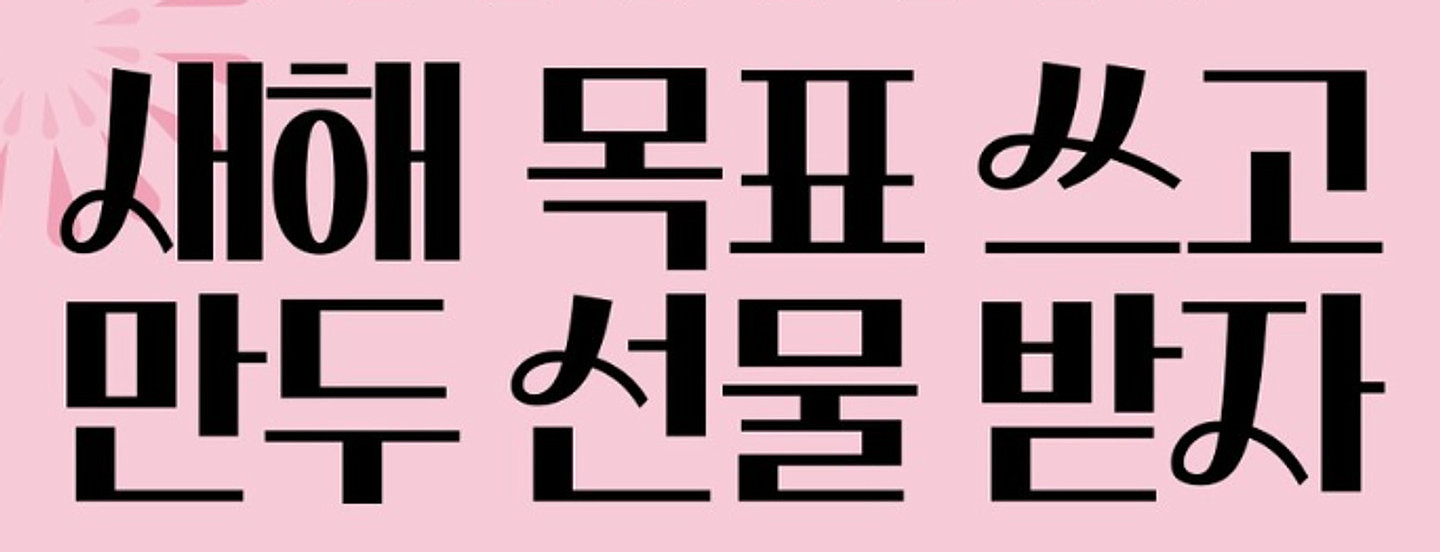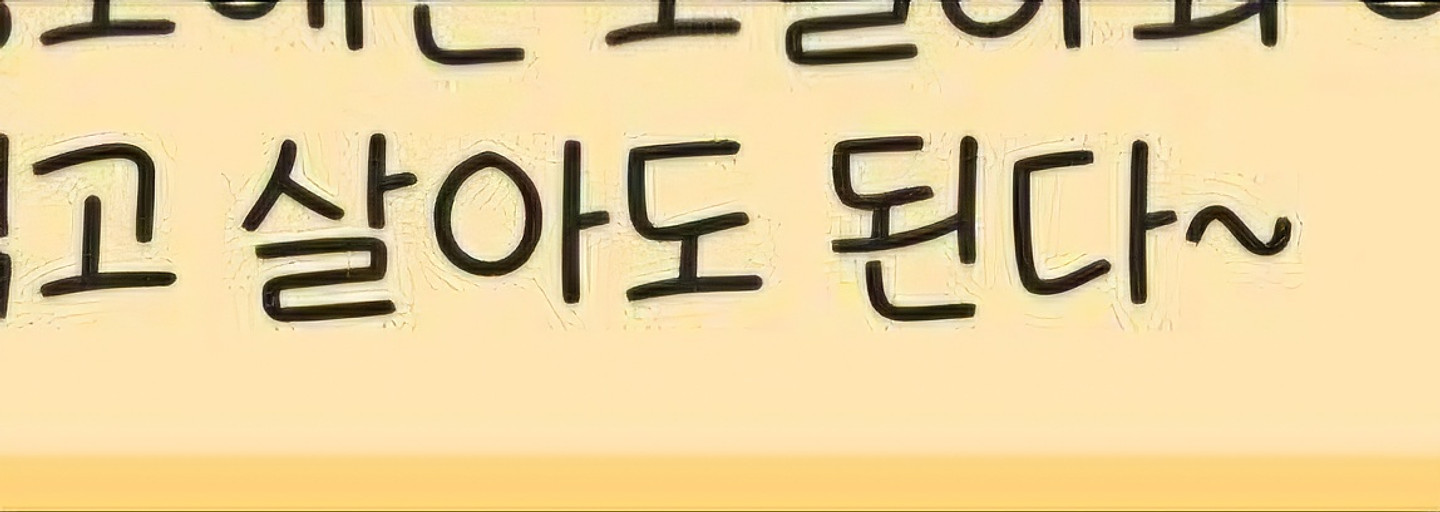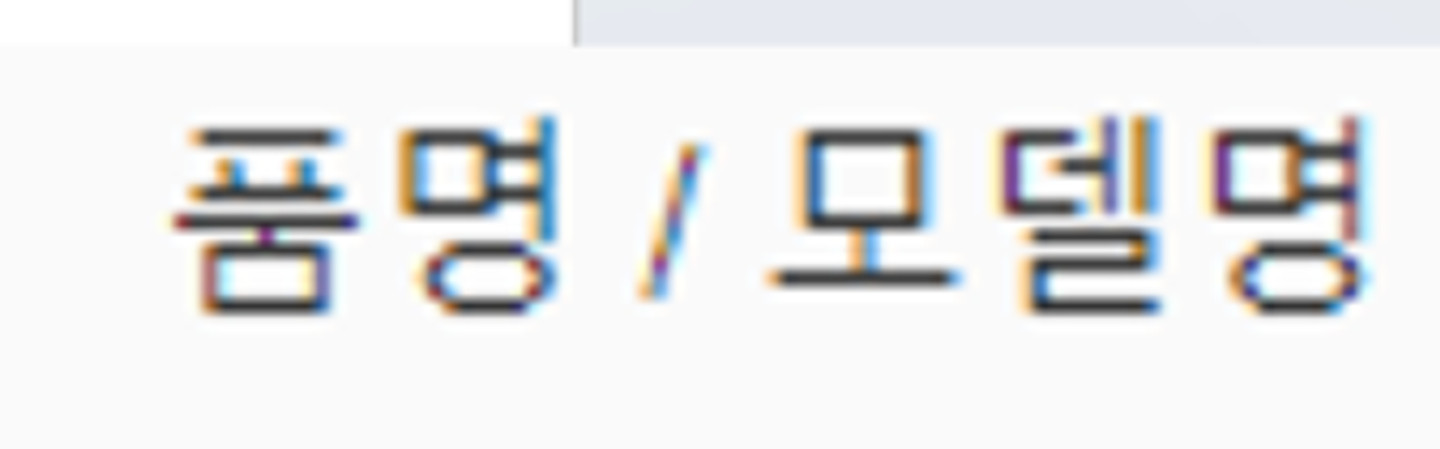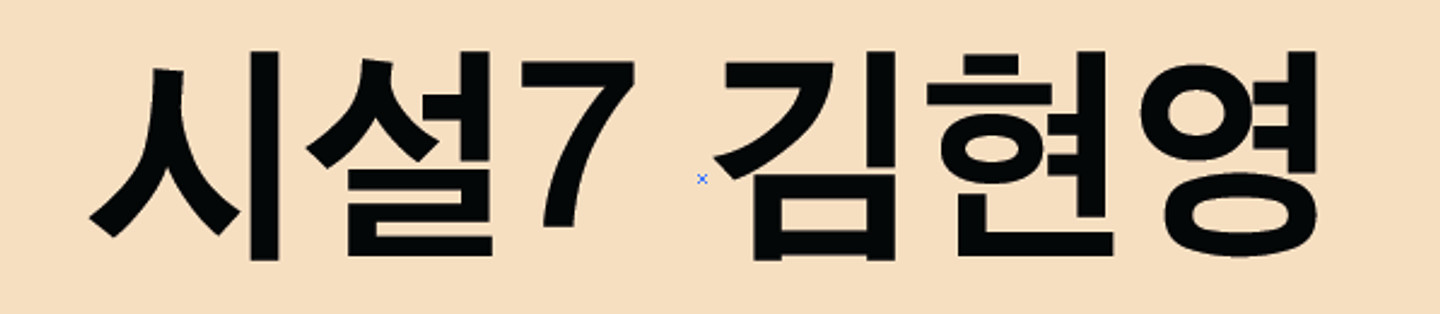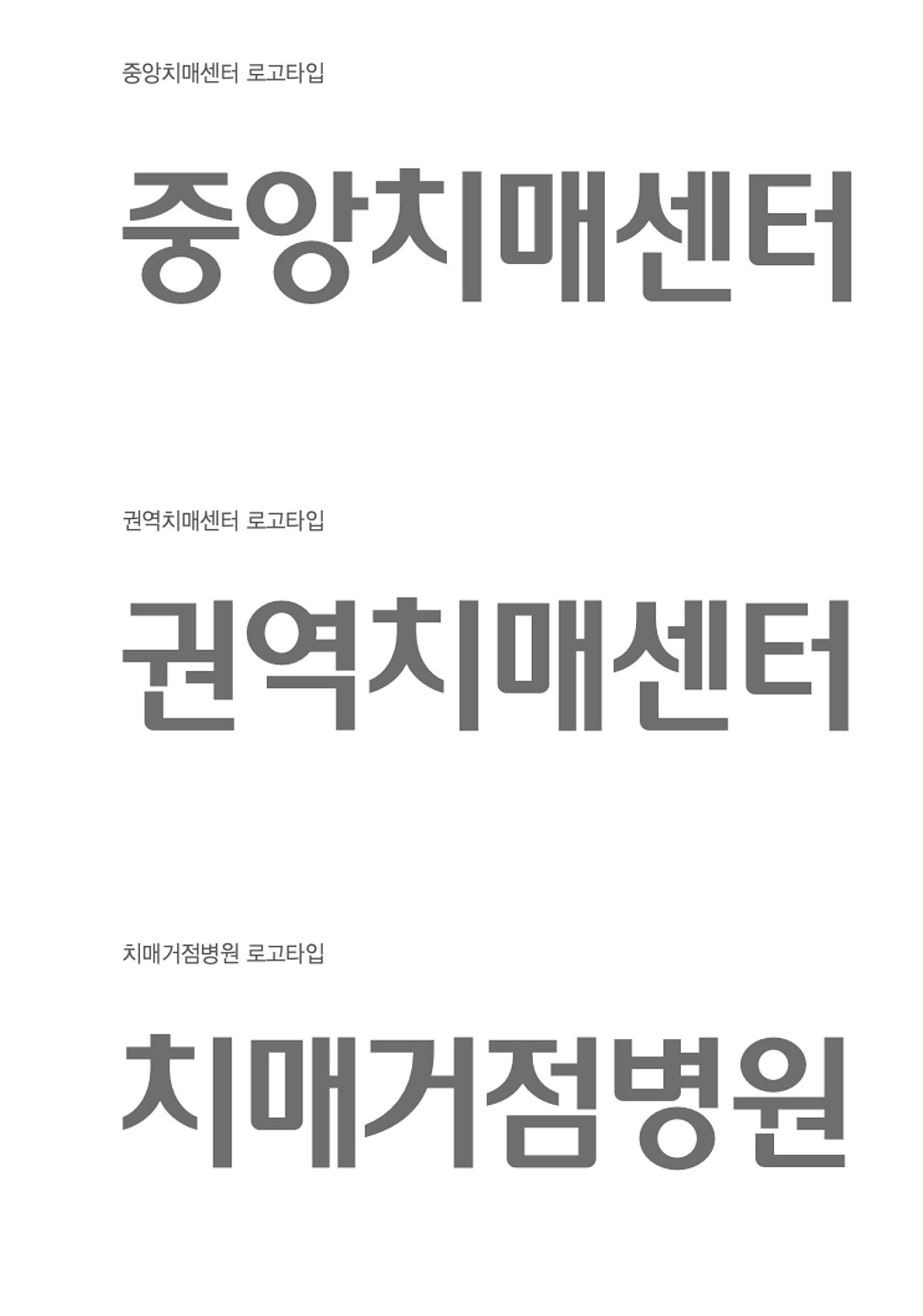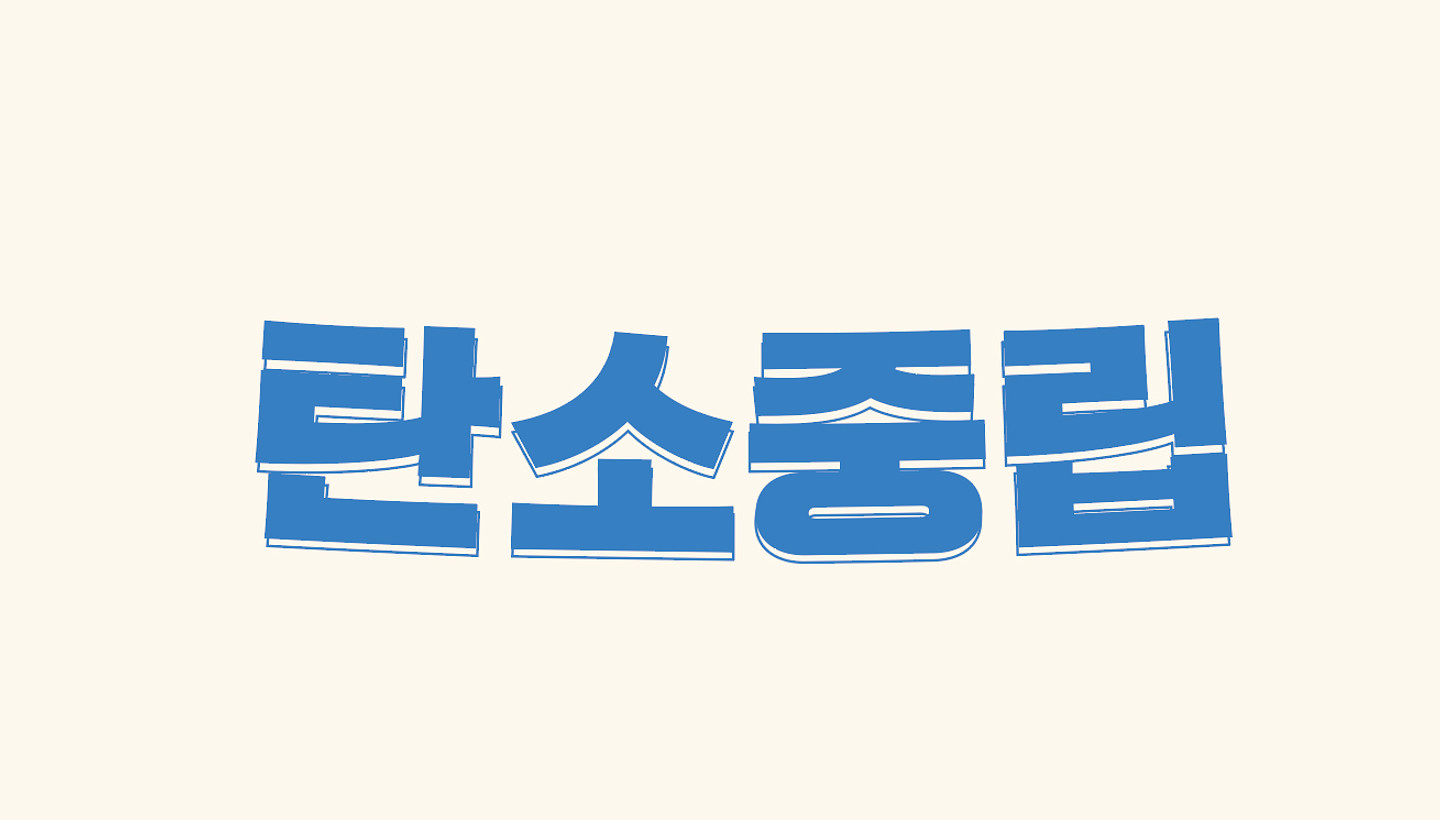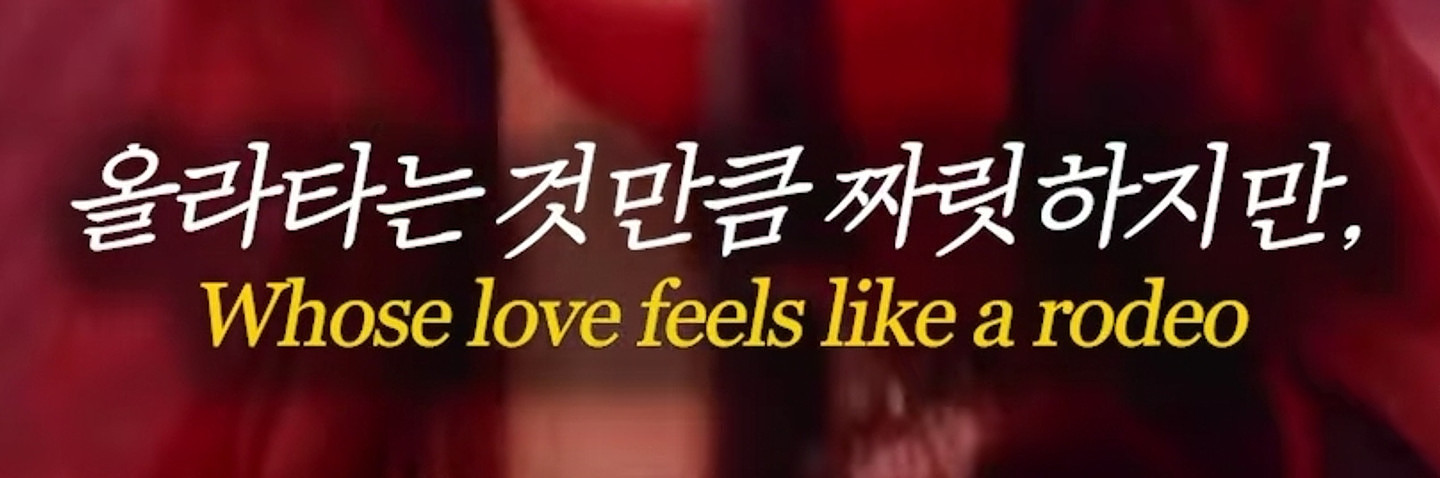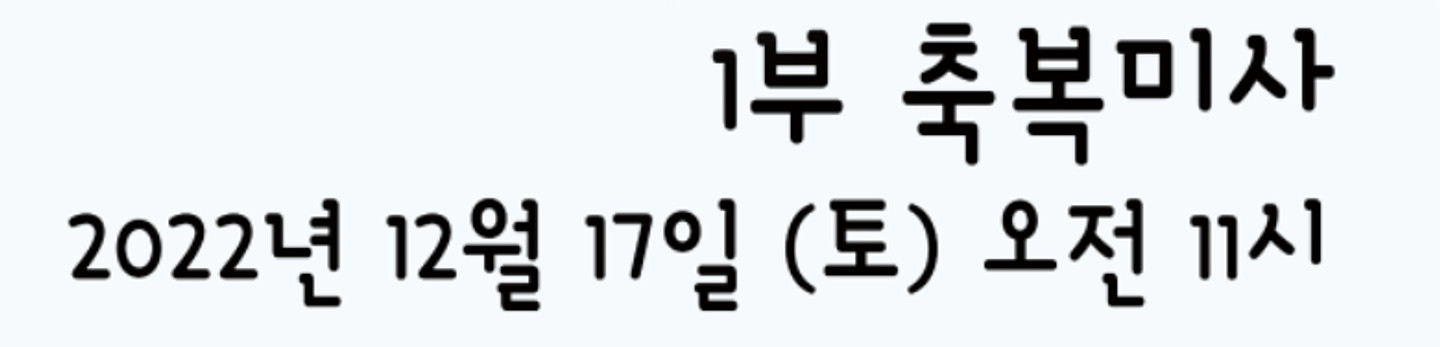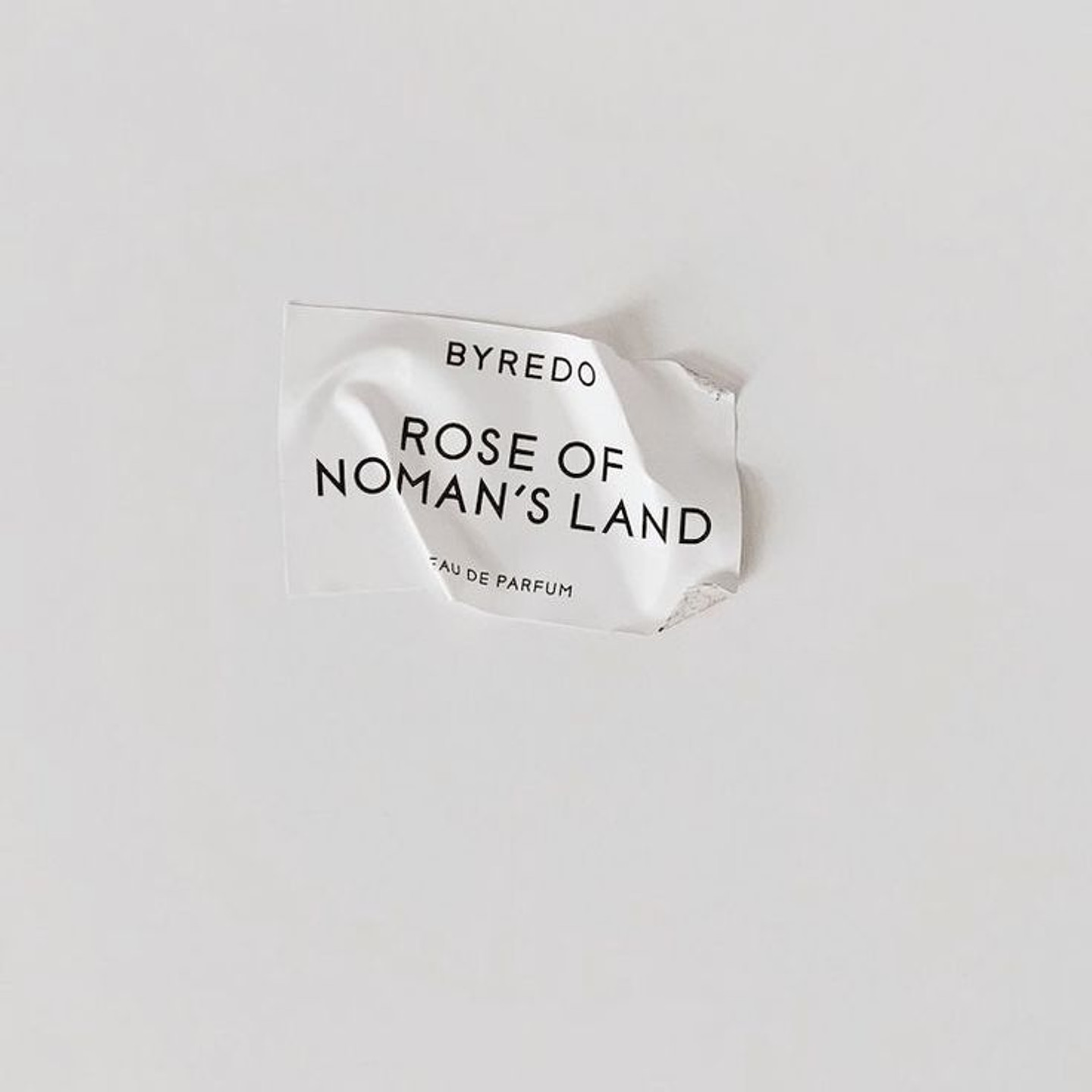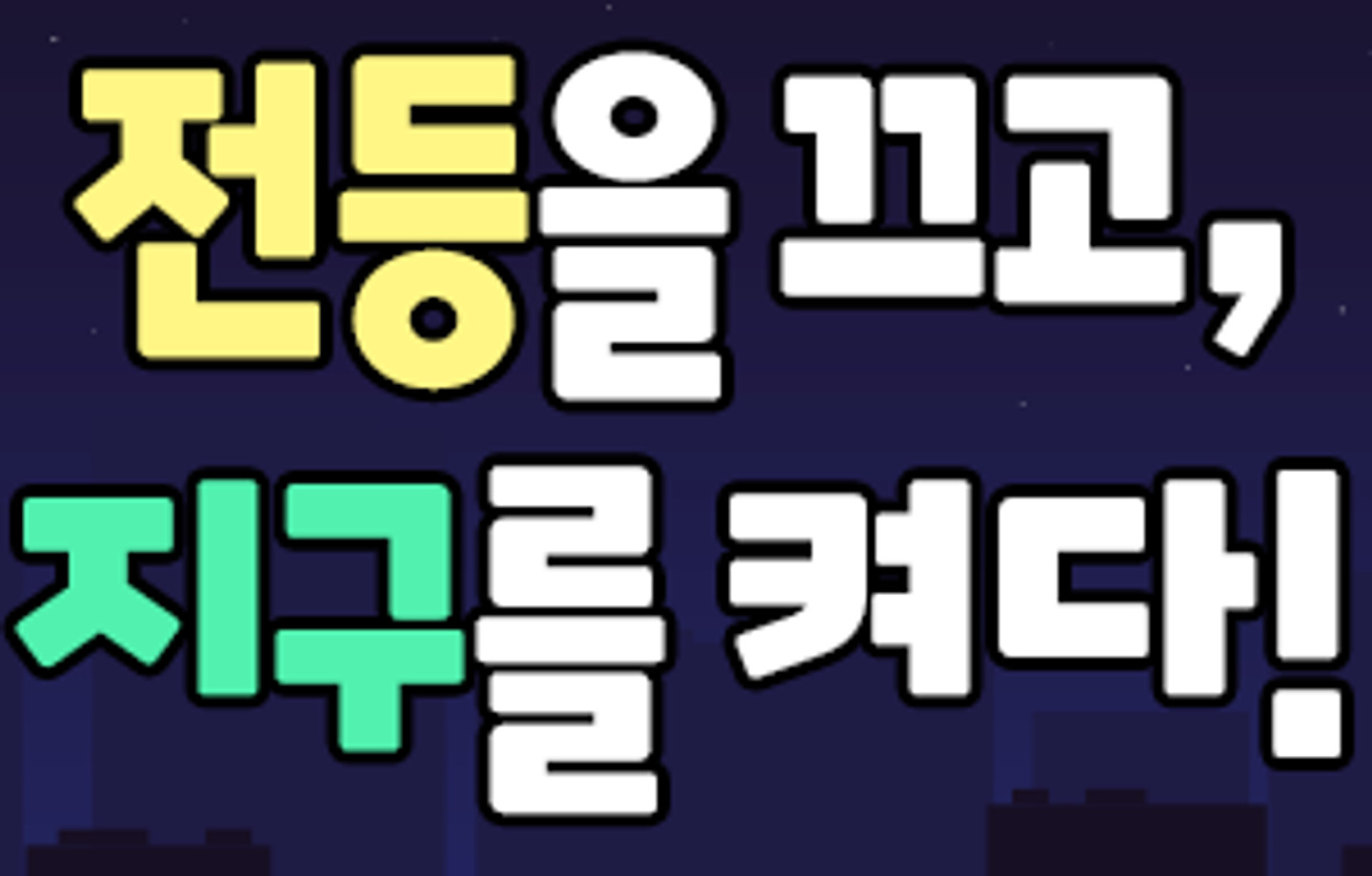
손글씨 느낌 나는데 무슨 폰트인지 모르겠습니다 ㅠㅠ!! 찾아주시는 분께 미리 감사 인사드립니다!
무슨 폰트인지 아시는 분 계실까요?
랜더스샵 홈피에서 따와서 폰트가 잘 보이게 수정했습니다.. 무슨 폰트인지 알수 있을까요??
DP예고편에 있는 폰트인데 제발 알려주세요 ㅜㅜ 글자에 있는 얼?룩 같은건 글꼴로 되는게 아니겠죠? ㅜ
무슨폰트일까요..?
’돌아다닐때마다~종이가방‘ 자막 폰트 알려주세요!
무슨 폰트인가요ㅠㅠ
폰트 궁금합니다~
캡컷에 있는 고딕체인데 뭔가여
이건 무슨 폰트인가요?
알려주세요 폰트고수님들!
이 폰트는 무엇일까요?
중간에 있는 HIGH TOP 폰트가 궁금하네요.. 다른 한글 폰트는 다 아는데, 영문폰트만 알려주세요
폰트 좀 찾아주실 수 있나요ㅜㅜ
혹시 (유튜브) 핫소스 로고 폰트가 뭔지 알 수 있을까요?궁금합니다
무슨 폰트인가요 ?
로마 숫자 'MMXXV'의 폰트가 무엇인지 궁금합니다.
이 폰트 무엇인가요...
이게 대체 무슨 폰트일까요..? 비슷한 폰트로 팔칠엠엠 일상, 부르크 고딕, 밀양아리랑고딕, 온고딕, 아리따돋움 다 찾아봤는데 아니네요..ㅠ 그냥 돋움체인가 하는 생각도 드는데 여기 계신 폰트척척박사님들께 혹시라도 여쭤봅니다....!
이 폰트 뭔가요 ㅜ ?
존이야박이냐 유튜브 자막 폰트 알려주세요 한글, 영어 둘 다요!
이거 무슨 폰트일까요ㅠ
이 폰트 아시는분 계실까요??
동글동글 너무이쁘다 무슨폰트?
영화 영웅에 나오는 이 글씨체 같은 폰트 있을까요?
류스펜나님 영상 속 폰트 뭔지 아시는분??!!
릴카 영상입니다 폰트 뭔지 알 수 있을까요?
어떤 폰트인지 궁금합니다...!
이거 무슨폰트인가요?무료비슷한 폰트좀알려주세용 ㅠㅠ
혹시 이 폰트처럼 테두리에만 색이 칠해진 폰트 좀 알려주시면 감사하겠습니다
정말 궁금해서 그러는데 이 폰트 아시는분??
이 폰트가 무엇인지 알고 싶습니다..
이 폰트 아시는분??
이 폰트가 뭘까요?
이 폰트가 무엇인지 알 수 있을까요??
가운데 메인 글씨 폰트 궁금합니당 ...
저는 여기서 믿고 구매해요 폰트 뭔지 알려주실분 ㅠ🙏🏻
카누 바리스타 광고 이 글씨체 뭘까요???
너무 달아. 폰트가 궁금해요~
이거 무슨 폰트일까요??
이 폰트 뭐에요? 큠갤에서 다운받으려고갔더니 안되던데
급합니다 !! 이 폰트 뭔가요?
이 글꼴 찾아주세요!! 부드러운 궁서체랑 손글씨랑 섞인 것 같은,…
위에 손글씨같은 폰트랑, 아래 각진 폰트 궁금합니다!
이거 무슨 폰트인가요?ㅜ
무슨폰트인지 알려주세요 ㅜㅜ😢😢😢
위아래 글꼴 어떤걸까용? :)
Spoqa Han Sans Neo
폰트명 궁금해요